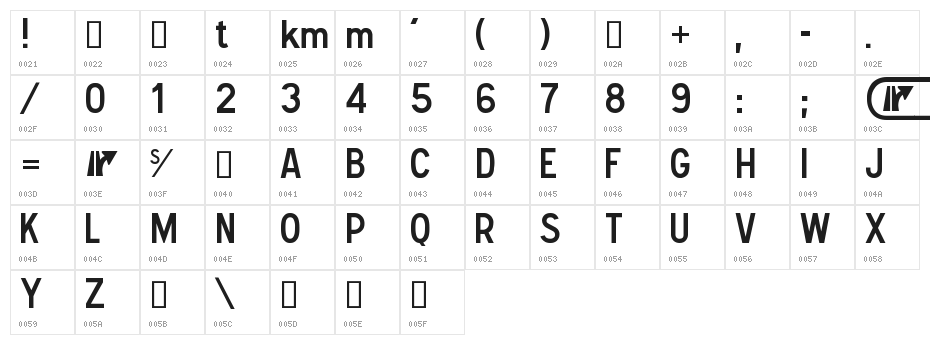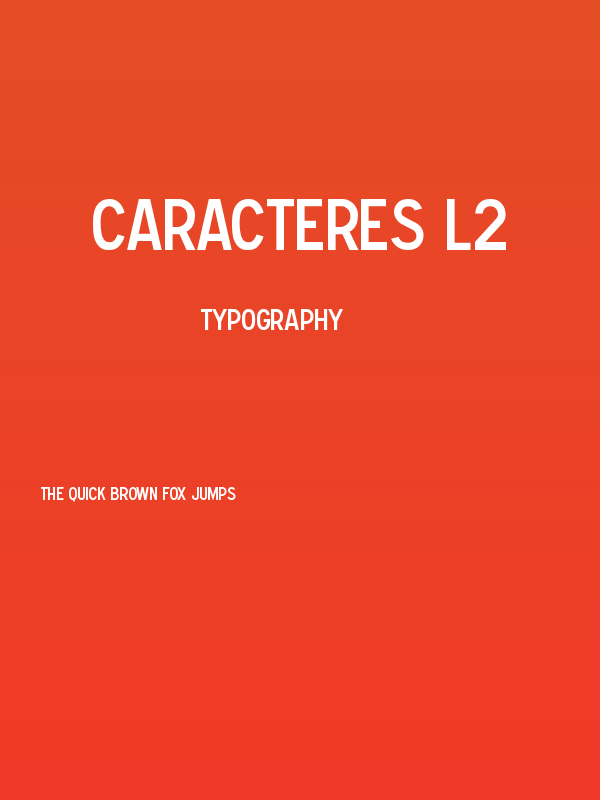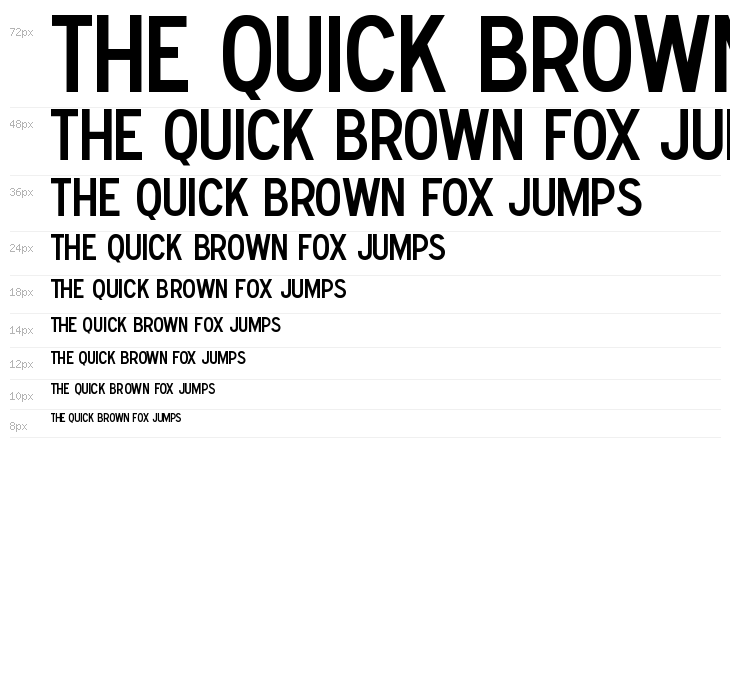
Caracteres L2 Font
| Anwendungsfall | Headlines, Logos, Digital interfaces |
| Vorgeschlagene Projekte | Ideal for branding, advertising, headlines, and digital interfaces due to its bold and clear appearance. |